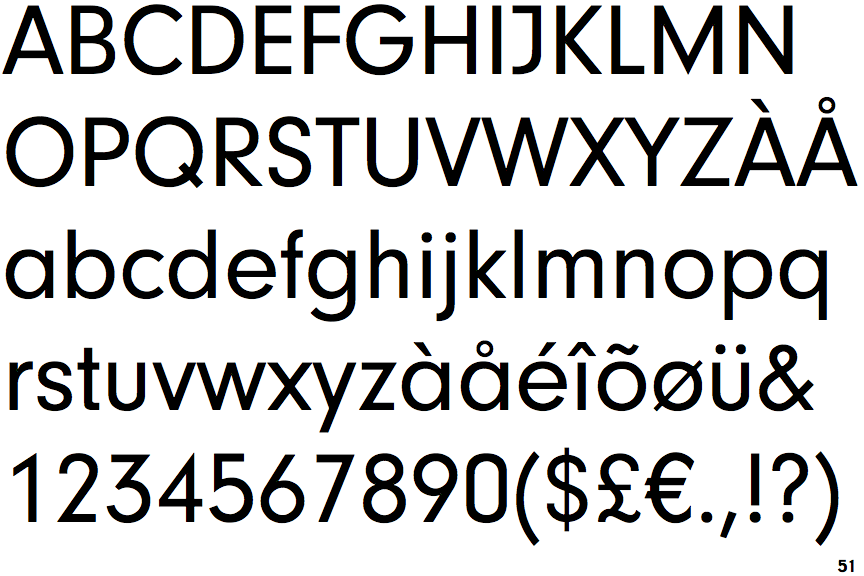
Faksimiles Stasi-Akten
ich erstelle gerade mit meiner Kollegin Faksimiles von Stasi-Akten.
Dank eines früheren Beitrags ( https://www.typografie.info/3/topic/34305-typografie-alter-ddr-akten/ ) habe ich schon alle Infos für die ältere Akte.
Die neuere Akte ist wohl aus den späten 80er Jahren. Ich suche die Schrift, die ihr auf dem Screenshot sehen könnt. Weiß einer welche Schrift das sein könnte. Bei meiner Recherche konnte ich nichts rausfinden.
Die Neuzeit Grotesk ist es auch nicht. Das kleine g ist anders.
Ich habe bisher keine Schrift gefunden, dessen "g" so aussieht wie auf dem Screenshot. Aber vielen Dank schon einmal.
Leider keine bessere Auflösung, nur noch das große R. Sonst muss ich es mir basteln. Allerdings hätte ich gedacht, dass doch irgend jemand wissen müsste welche Schriften die Stasi in ihren Akten verwendet hat.
Und die Unterlänge vom g stimmt auch. Etwas gedrungen und sehr rund.
Es wird wahrscheinlich tatsächlich so sein. Ich hatte die Super Grotesk eigentlich auch gleich ausgeschlossen. Aber wenn man sich bestimmte Buchstaben anschaut, z. B. auch das "R" wird es wohl diese Schrift sein.
Ich denke auch, dass es sich um die Super-Grotesk handelt. Der i-Punkt wurde wahrscheinlich im Bleisatz nicht sonderlich gut gereinigt und ist deshalb unsauber im Druck.
Jeder Auftraggeber einer Druckerei mußte das nehmen, was die Druckerei hatte. Eine Konstante im Unternehmen war in der Schrift nicht immer durchzuhalten, wenn mehrere Druckereien an verschiedenen Standorten druckten. Ob die Stasi beispielsweise in Leipzig aus derselben Druckerei beliefert wurde wie die Stasi in Berlin, weiß ich nicht. Die großen Druckereien hatten aber alle die Super-Grotesk im Kasten.
Bei der Schrift handelt es sich um die Super-Grotesk, im Druck leicht abgequetscht, der Buch-Schnitt oder der halbfette. Wenn das Bild aus den späten 80ern ist, wird der Aktendeckel aus einer großen Druckerei kommen. Zwar druckten auch kleinste Betriebe gelegentlich für die Stasi, aber eher Schnellschüsse in kleinen Auflagen. In den großen Betrieben hielt man Bleischriften vorrätig, die nachgeliefert werden konnten von Typoart. Die Super war die Universal-Serifenlose der DDR. In der kleinen Werkstatt, in der ich Setzer war, hatten wir die Fundamental und Kristall im Kasten. Und mein Meister berichtete gelegentlich Anekdoten, wie die Stasi bestimmte Aufträge drucken ließ und dann mit zwei Leuten solange in der Werkstatt herumlungerte und aufpaßte, bis die Sachen fertig waren und gleich mitgenommen wurden. Um eine Schriftkonstante der Behörde ging es dabei nicht. Wenn es serifenlos sein sollte, kam für eine Behörde in den 80er Jahren in unserer kleinen Setzerei sicherlich die Fundamental zum Einsatz. Der Laie sieht kaum die Unterschiede. Ob die Stasi einen Künstlerischen Leiter hatte, der sich um so etwas kümmerte? In der Regel bekamen wir hand- oder maschinengeschriebene Vorlagen von den Kunden, mein Meister schrieb rasch nach kurzer Überlegung die Satzanweisung daneben, und ich entzifferte dann ggf. das Gekrakel des Manuskripts (wörtlich des Handgeschriebenen) und setzte. – Formulare, Aktendeckel und dergleichen gingen nicht durch Hände von Grafikern. Man machte das so, wie man es bei ähnlicher Gelegenheit für andere Betriebe und Behörden gemacht hatte.
Ich glaube auch, das einzige, was hier Fakt ist, ist: "nach dem Zweiten Weltkrieg griff der VEB Typoart in der DDR auf die noch vorhandenen Matrizenbestände zurück."
Und dann war es einfach logisch, dass man dann, wenn immer man Schriften benötigte, auf das zurückgriff, was entweder in der Setzerei noch im Bestand war, oder man eben im Lande fertigen konnte.
Das hat man ja eigentlich überall so gemacht.